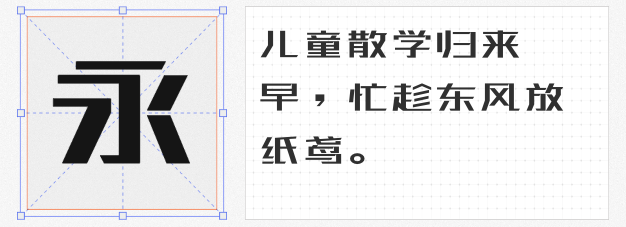
在海报设计的视觉语言中,字体不仅是信息传递的载体,更是情感表达的媒介。以下四款免费商用字体,以独特的美学基因与实用性能,为设计师提供了突破常规的创意工具。
这款字体以机器学习复刻《爨宝子碑》的书法精髓,将隶书的方笔劲道与楷书的结构秩序融为一体。其三角点折弯与横画“雁尾”设计,形成外露锋芒的视觉张力,而险峻的骨架与大胆的布白,则打破传统均衡,在“失度”中暗藏艺理。
历时四年打磨的无衬线字体,以1:0.84的字宽比例重构汉字形态,通过笔画粗细的权重分配与12度倾斜末端设计,赋予字体年轻硬朗的科技感。其扁平化结构与高辨识度,使其成为科技产品海报的首选——无论是智能硬件的极简风,还是互联网品牌的未来感,都能通过字体的锐利线条与动态节奏精准传递。
由79位设计师众包完成的这款字体,以“横细竖粗”的经典黑体为基础,通过10:7的长宽比与扁平化结构,创造出锐气与沉稳并存的独特气质。其笔画末端的统一倾斜角度与简洁有力的笔势,使标题文字在海报中形成视觉焦点。
这款由150位设计师共创的字体,以灵活多变的笔画粗细与俏皮结构,构建出充满童趣的视觉语言。其适用场景覆盖从母婴产品到节日营销的广泛领域:在儿童节海报中,字体的活泼感可拉近与受众的距离;在零食包装设计中,其轻松氛围又能激发消费欲望。
这四款字体以免费商用的开放姿态,为设计师提供了从文化深度到科技未来、从力量美学到情绪价值的多元选择。无论是追求传统与现代碰撞的创意实验,还是需要快速传递品牌调性的商业项目,它们都能成为打破同质化设计的关键变量。